亜細亜の漢字ロゴデザイン
グラフィック社は、Viction:ary編集による、デザイナー、文字好き、フォント好き必見の日・中・韓の漢字タイポグラフィを大量コレクションしたデザインブック「亜細亜の漢字ロゴデザイン」を、2023年1月に発売した。
「亜細亜の漢字ロゴデザイン」では漢字を用いた最新のグラフィックス/ロゴデザインと実際の採用例を紹介。
日本、中国、台湾、香港、韓国など、アジア各国の漢字タイポグラフィ、フォントデザインの新作がたっぷり収録されたデザインブック。
漢字にしかないユニークな表現を追求した作例満載「亜細亜の漢字ロゴデザイン」
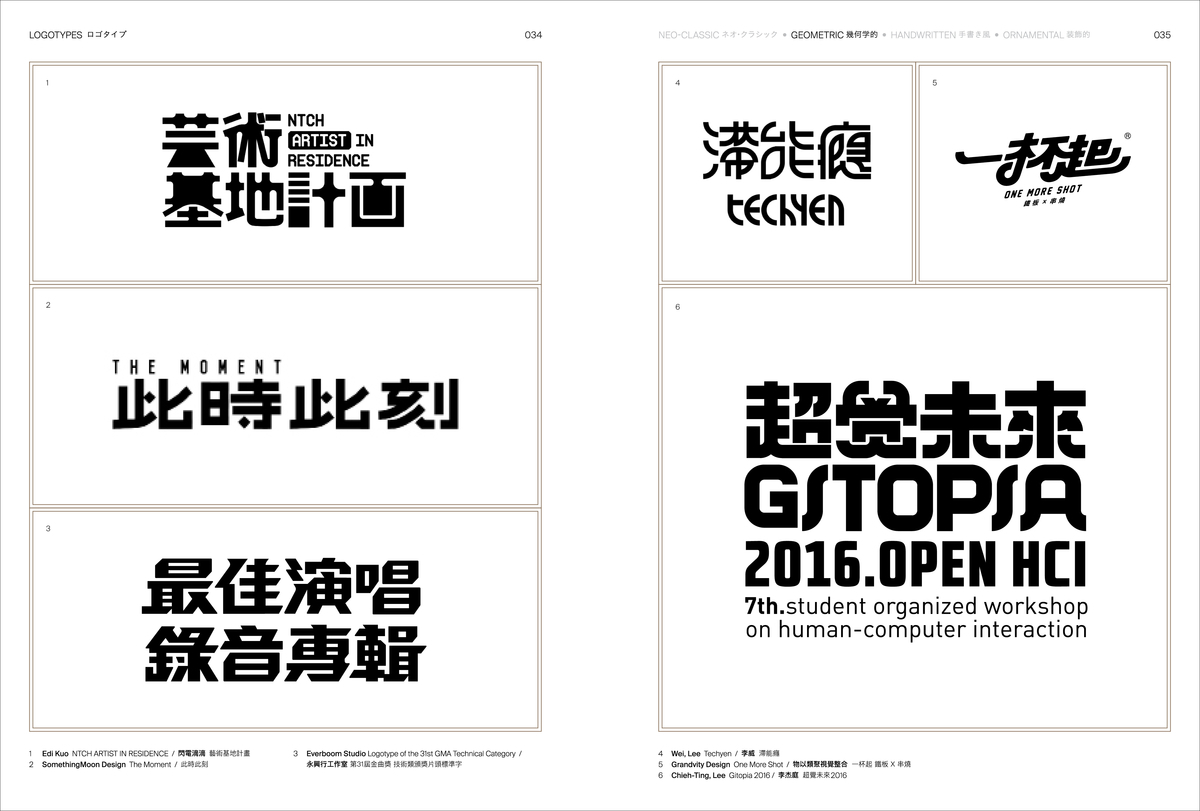
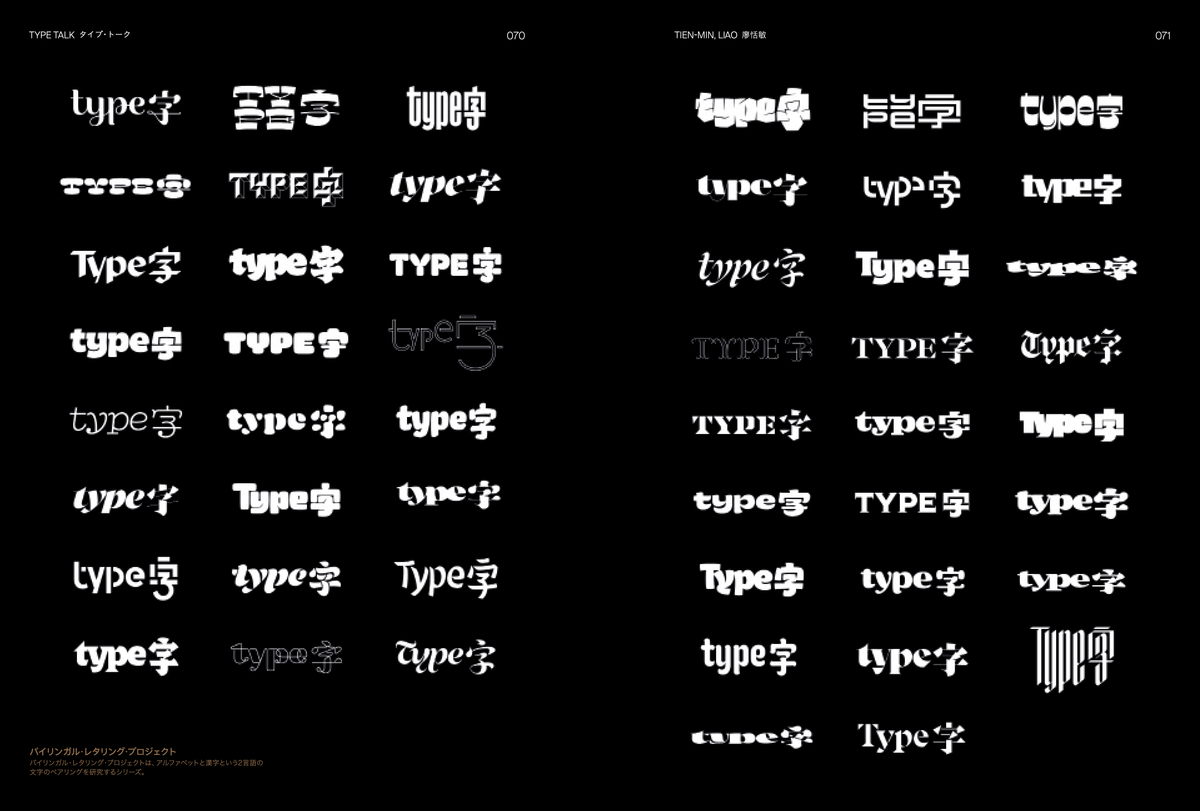
「亜細亜の漢字ロゴデザイン」では、ロゴからフォントまで、100以上のプロジェクトを掲載。
ロゴタイプ、ブランド・アイデンティティ、広告、印刷物を豊富な実例とともに紹介。
どれも、古代に生まれた文字を現代的でフレキシブルなデザインの要素へと変身させ、抽象的なコンセプトを具体的な視覚表現として打ち出しているものばかり。
ロゴタイプのヒントやアイデアが満載「亜細亜の漢字ロゴデザイン」
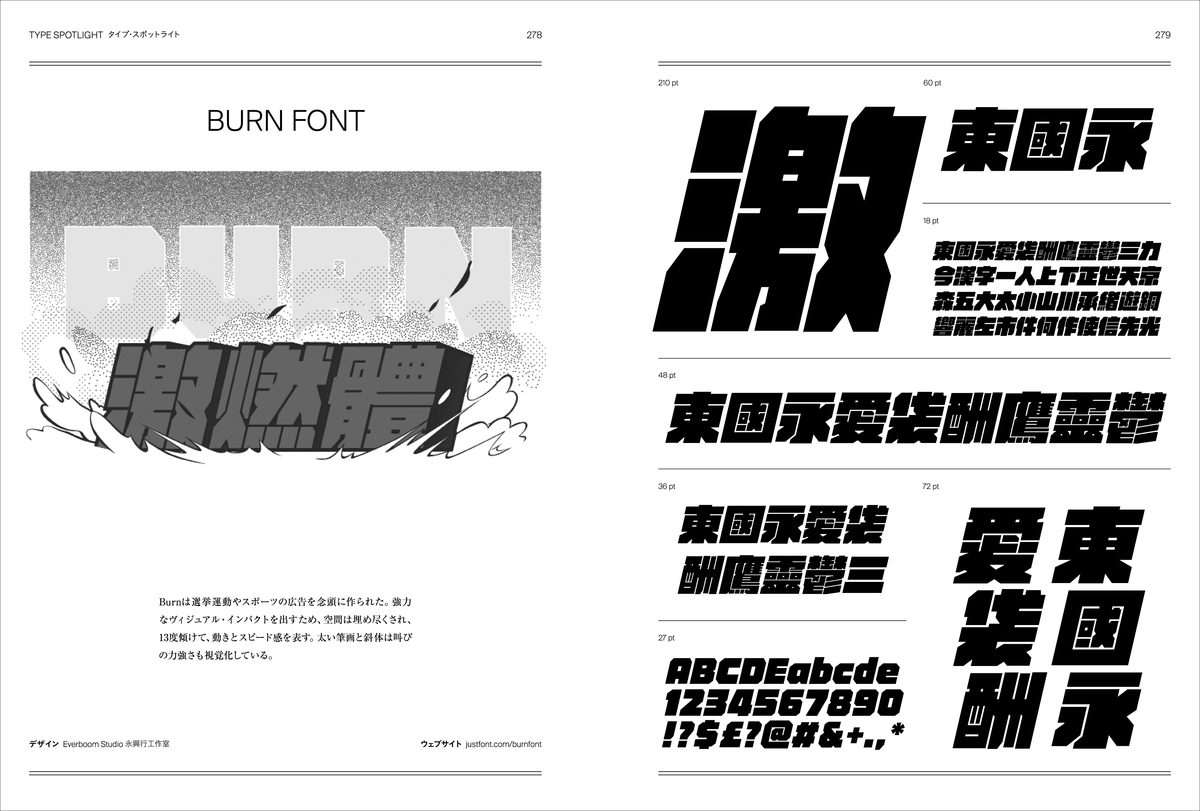
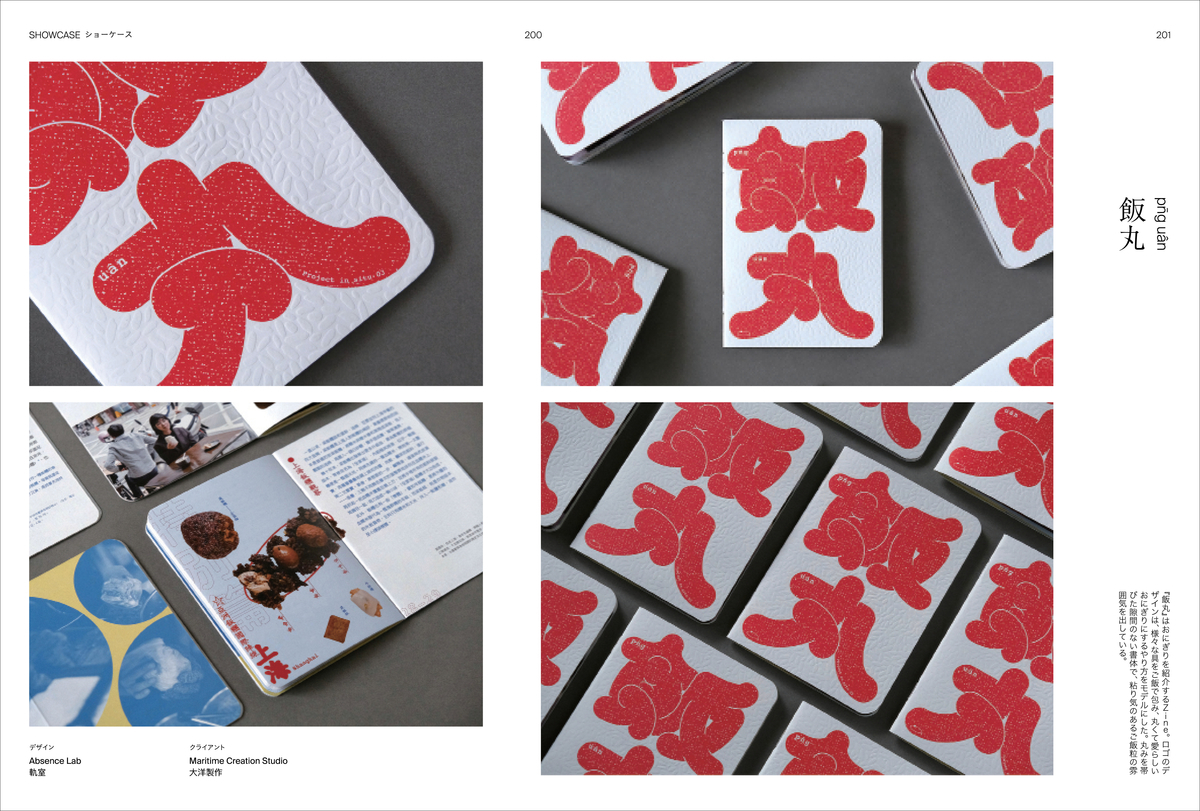
ブランディング・プロジェクトや展示会のビジュアル・アイデンティティ、多様性あふれる文字デザインとそれを様々に応用したクリエイティブな個人作品を紹介するほか、個性溢れる新作漢字フォントの活字見本なども掲載。
豊富な作例や新進気鋭のデザイナーたちのインタビューには、フォントデザイン、ブランディングに関わる全ての人のためのヒントやアイデアがあふれている。
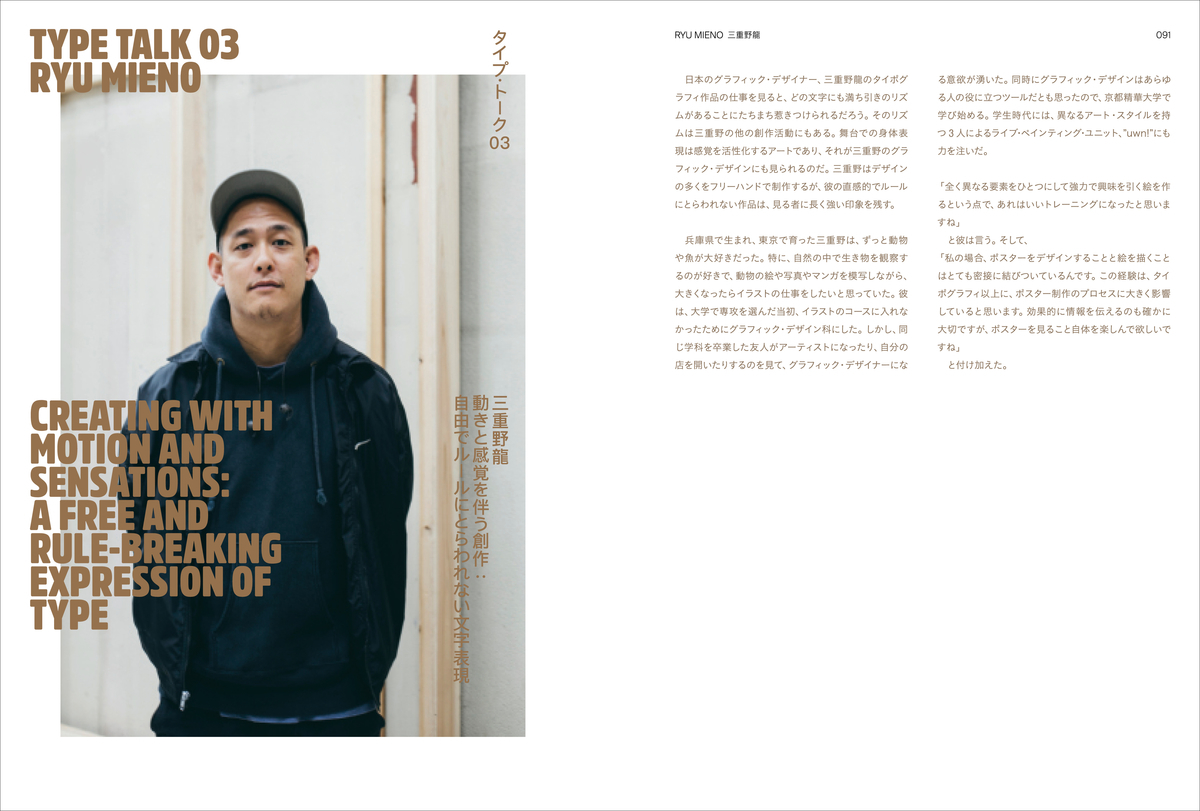
「亜細亜の漢字ロゴデザイン」目次
推薦の辞、まえがき、ロゴタイプ(ネオ・クラシック・スタイル、幾何学的スタイル、手書き風スタイル、装飾的スタイル)、タイプ・トーク(Tien-Min Liao、Julius Hui、三重野龍、justfont)、ショーケース、タイプ・スポットライト、作者略歴・作品クレジット